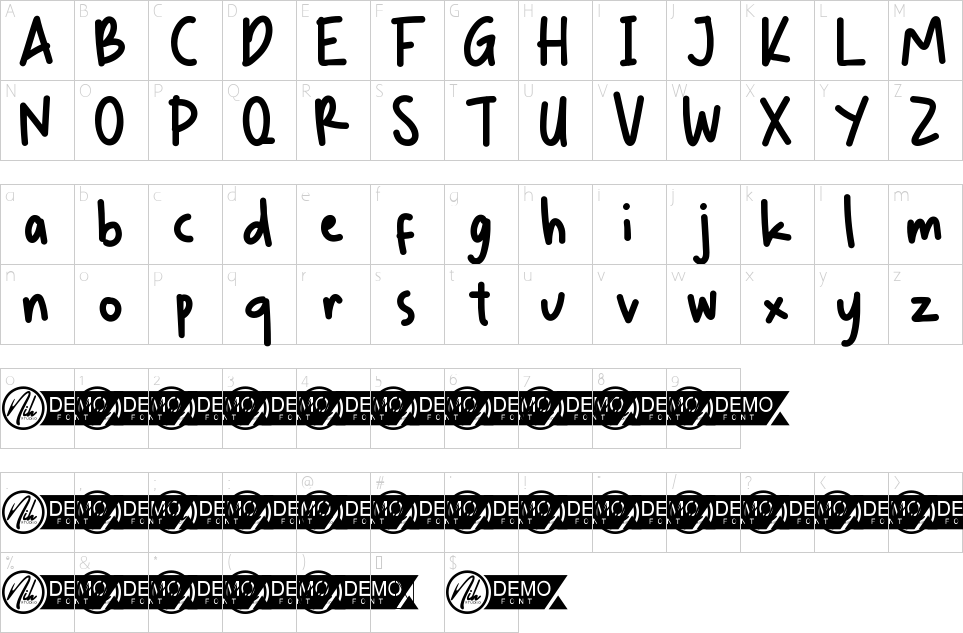
A fonte Melawan Rindu é uma grata surpresa para designers gráficos em busca de novas opções para seus projetos, especialmente aqueles que buscam uma fonte com uma elegância suave e uma personalidade única. Desenvolvida pela NihStudio, esta fonte foi projetada para oferecer uma experiência de escrita agradável, com uma tipografia cuidadosamente elaborada que transmite sutileza e emoção. Com seu design cuidadosamente pensado, a Melawan Rindu não apenas adiciona um toque único aos seus trabalhos, mas também proporciona uma boa leitura, mesmo em tamanhos menores. Em um momento em que as fontes gratuitas são cada vez mais importantes para designers que procuram economizar tempo e recursos, o Melawan Rindu atende perfeitamente essa necessidade, sendo uma fonte de download fácil para quem quer explorar novas possibilidades gráficas. Com apenas 1.633 downloads em seu perfil, é uma fonte que merece uma olhada mais atenta, especialmente para aqueles que buscam um toque personalizado e sofisticado em seus projetos.